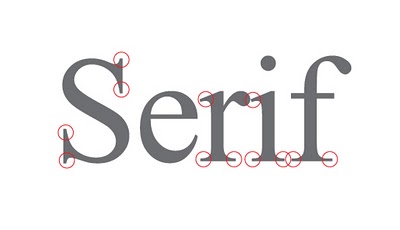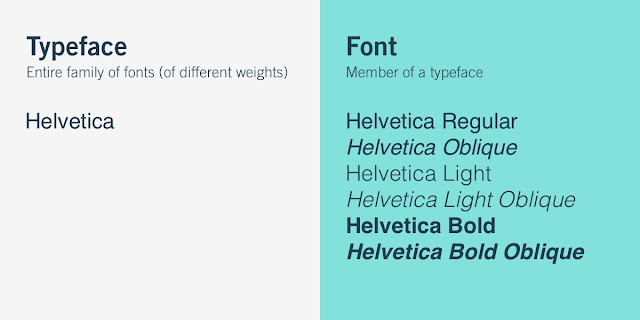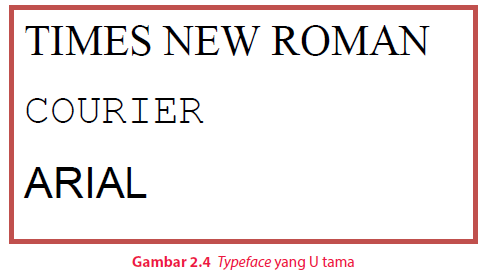
Font adalah representasi grafis dari teks yang dapat menyertakan jenis huruf ukuran titik berat warna atau desain yang berbeda berdasarkan simpulan kami yang mengacu pada sumber situs computerhope.
Font atau typeface adalah istilah yang digunakan untuk. Garamond ini merupakan jenis font yang sudah ada sebelum digunakannya font times new roman. Cara mendeteksi font what the font juga sangat mudah. Umumnya huruf italic digunakan untuk teks dalam jumlah yang tidak terlalu panjang seperti untuk keterangan gambar caption highlight dari naskah copy blurb. Sedangkan font merupakan suatu kumpulan lengkap dari huruf angka simbol atau karakter yang memiliki ukuran dan ciri tertentu.
Postscript font dan truetype font adalah huruf elektronik atau yang disebut font. Untuk jenis font arial untuk judul umumnya adalah berukuran 12 14 dan untuk. Yaitu ikon untuk pengaturan ukuran besarnya huruf dalam font yang digunakan pada pengetikan. Perancang font copperplate sejatinya menginginkan font ini untuk digunakan hanya pada header atau judul.
Scientific american magazine merupakan salah satu lembaga yang menggunakan typeface ini. Program software perangkat lunak seperti microsoft word microsoft excel dan wordpad memungkinkan pengguna untuk mengubah font yang digunakan saat mengetik teks dalam. Standar ukuran font yang umumnya digunakan adalah untuk jenis font times new roman adalah unt u k judul 14 sd 16 dan untuk text dalam paragraph adalah berukuran 12. Istilah ini penting untuk diketahui agar tidak lagi terjadi salah persepsi dalam masyarakat apalagi dalam dunia desain.